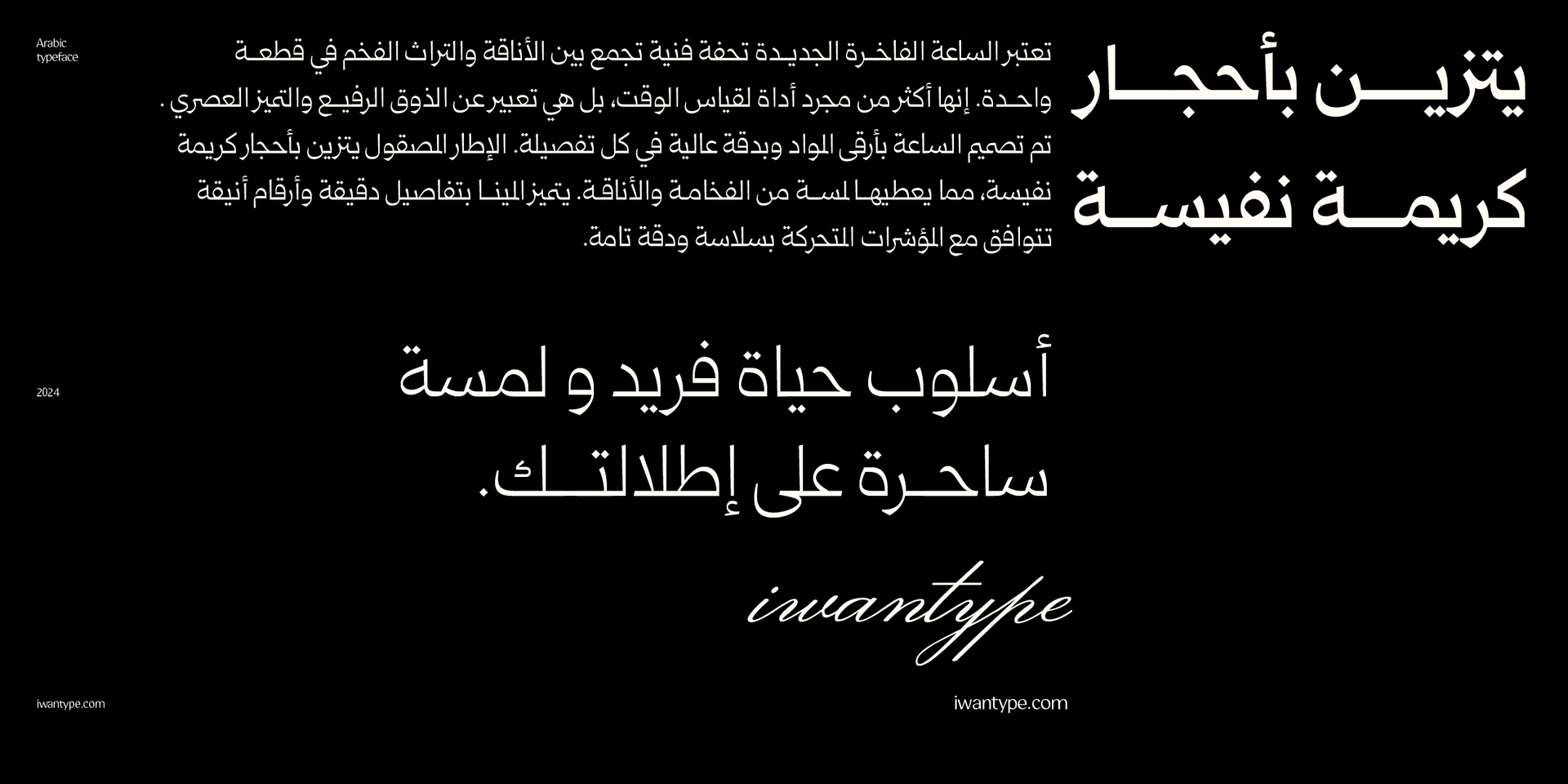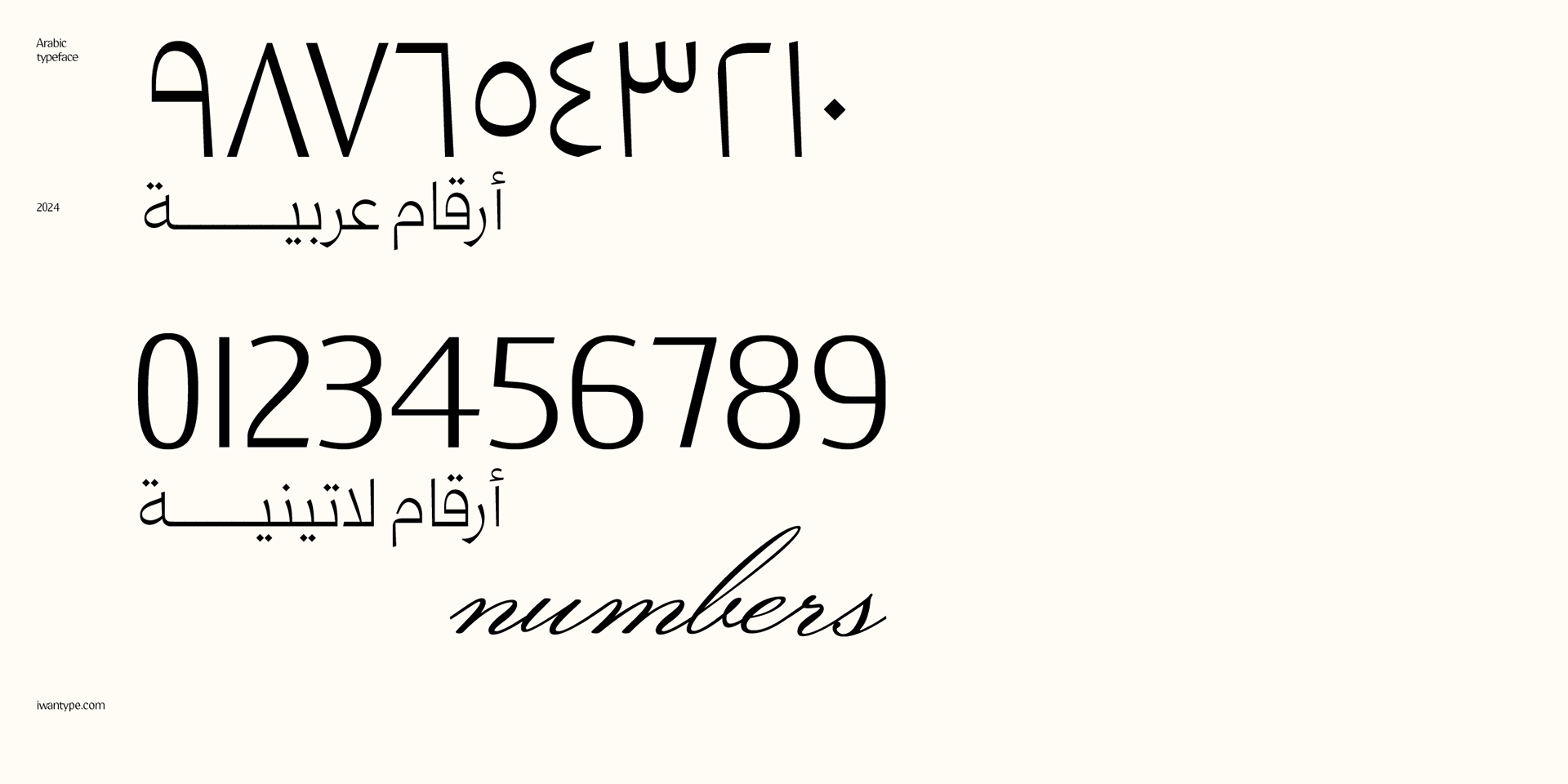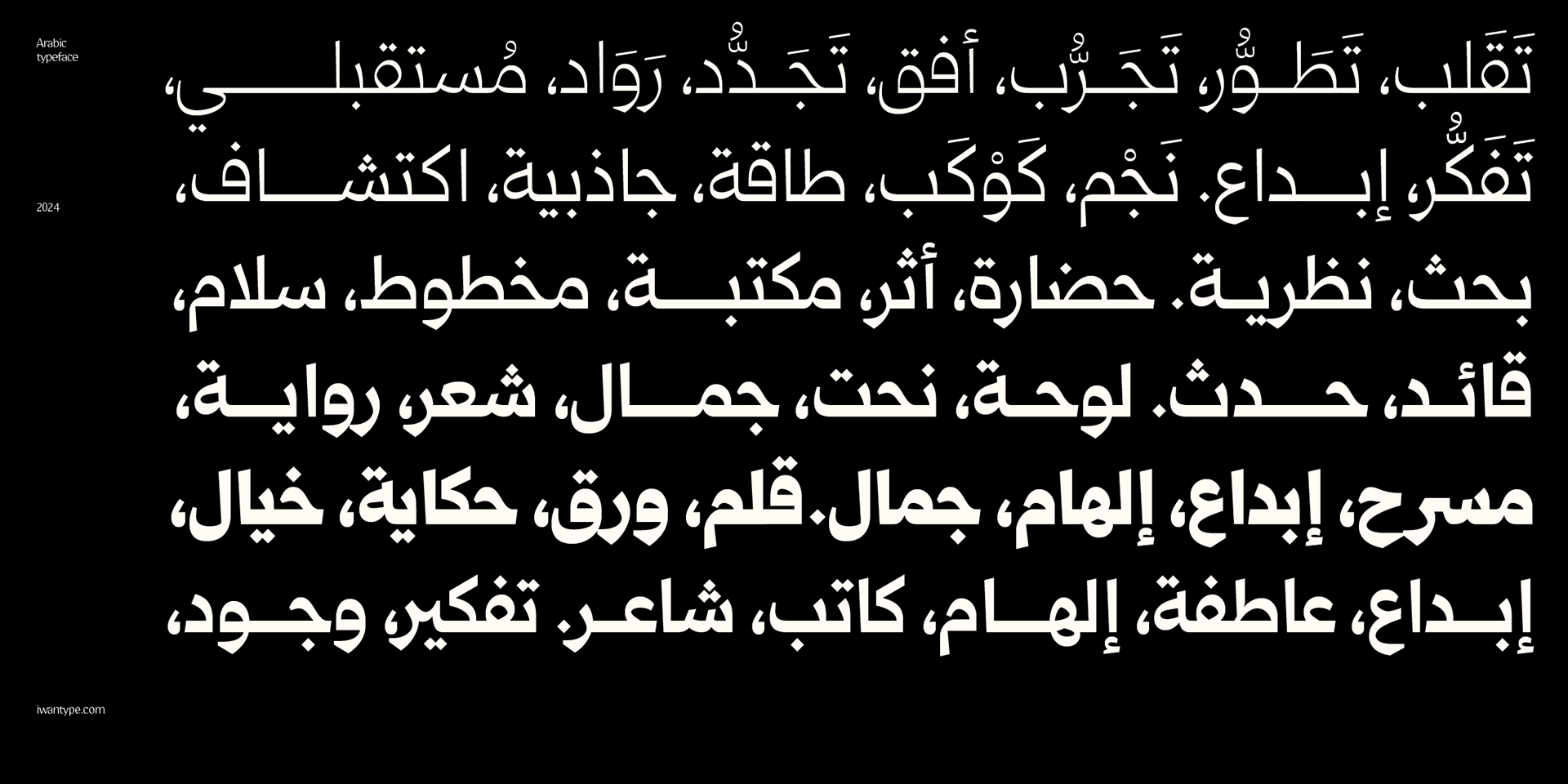
Qomra Arabic typeface - خط قمرة الطباعي
الجمـــــال في البساطــــة والأناقـــــة
خط قمرة هو خط نسخ مسطري يجمع بين البساطة والأناقة في تصميم واحد مميز. يتميز بتفاصيله الواضحة وتصميمه الفريد، مما يجعله مثاليًا لمجموعة متنوعة من الاستخدامات
ميزات خط قمرة
تصميم مميز وأنيق: يتميز خط "قمرة" بتفاصيله الواضحة وتصميمه الذي يضفي لمسة من الأناقة على النصوص
خمسة أوزان متنوعة: متوفر بخمسة أوزان من خفيف إلى أسود، مما يمنحك مرونة كاملة في استخدامه لمختلف أنواع التصاميم والمشاريع
مميزات اوبن تايب: يحتوي على حروف مركبة، حروف مرسلة، ونقاط بديلة، مما يتيح لك إبداعًا أكبر في تصميم النصوص
تصميم مميز وأنيق: يتميز خط "قمرة" بتفاصيله الواضحة وتصميمه الذي يضفي لمسة من الأناقة على النصوص
خمسة أوزان متنوعة: متوفر بخمسة أوزان من خفيف إلى أسود، مما يمنحك مرونة كاملة في استخدامه لمختلف أنواع التصاميم والمشاريع
مميزات اوبن تايب: يحتوي على حروف مركبة، حروف مرسلة، ونقاط بديلة، مما يتيح لك إبداعًا أكبر في تصميم النصوص